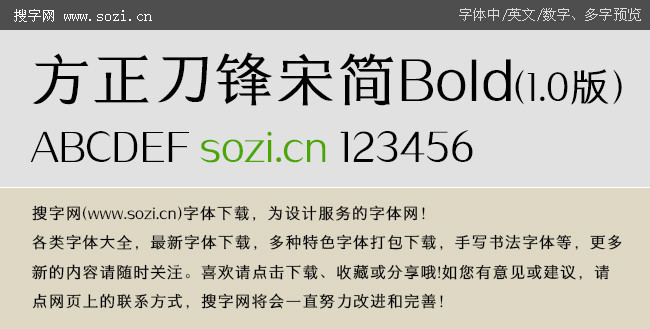
方正刀鋒宋簡Bold1.0
搜字網(wǎng)提供一款方正刀鋒宋簡Bold1.0中文字體下載,方正刀鋒宋簡是一款漂亮的宋體字體。由方正字庫全新開發(fā)的一款非常不錯的中文字體,該字體基于宋體而開發(fā)的,在宋體中的字角加入了銳利感,整體效果出色,適合書籍排版,海報設(shè)計(jì),包裝設(shè)計(jì)等應(yīng)用。(本字體為個人非商用版,如需要商用請聯(lián)系方正公司購買版權(quán))